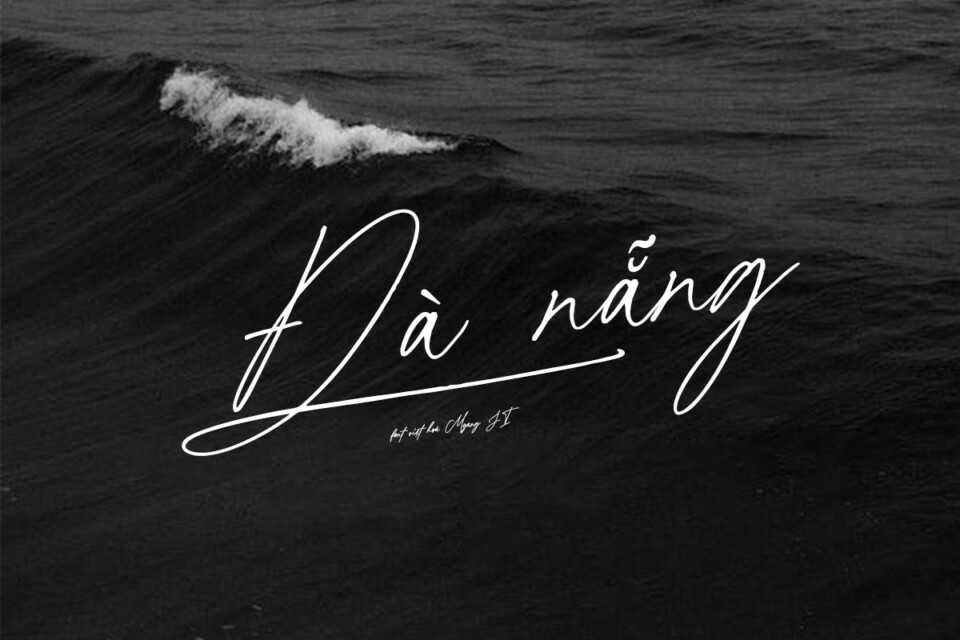
Font việt hoá MJ Donna Smith: Nét chữ viết tay thanh lịch cho thiết kế Việt
Giới thiệu về Font việt hoá MJ Donna Smith
Trong thế giới đồ họa, việc tìm kiếm một bộ Font Chữ vừa mang nét cá nhân hóa vừa đảm bảo tính thẩm mỹ cao luôn là ưu tiên hàng đầu. Font việt hoá MJ Donna Smith là sự lựa chọn hoàn hảo cho những ai yêu thích phong cách viết tay (handwriting) mềm mại và tinh tế. Bộ phông này không chỉ giữ nguyên được cái hồn của bản gốc mà còn được tối ưu hóa hoàn toàn cho bảng mã tiếng Việt, giúp người dùng dễ dàng sử dụng trong các phần mềm thiết kế phổ biến hiện nay.
Đặc điểm nổi bật của bộ font chữ này
Phong cách thiết kế độc đáo
Font việt hoá MJ Donna Smith nổi bật với những đường nét thanh mảnh, uốn lượn tự nhiên như được viết bởi một cây bút máy cao cấp. Khoảng cách giữa các ký tự được căn chỉnh tỉ mỉ, tạo nên sự liền mạch và nhịp điệu riêng biệt cho văn bản. Điều này giúp bộ font trở nên cực kỳ phù hợp cho các mục đích thiết kế thiệp mời, bìa sách hoặc các dự án nghệ thuật đòi hỏi sự sang trọng và ấm cúng.
Khả năng ứng dụng đa dạng
Nhờ quá trình việt hóa kỹ lưỡng, các dấu câu tiếng Việt trong Font việt hoá MJ Donna Smith được đặt vị trí chuẩn xác, tránh tình trạng lỗi font hay mất dấu khi gõ. Các bạn học sinh và giáo viên có thể sử dụng phông chữ này để làm bài thuyết trình, trang trí báo tường hoặc tạo ra những tấm thiệp chúc mừng đầy ý nghĩa. Đây thực sự là một công cụ đắc lực để biến những ý tưởng sáng tạo thành hiện thực một cách sinh động nhất.